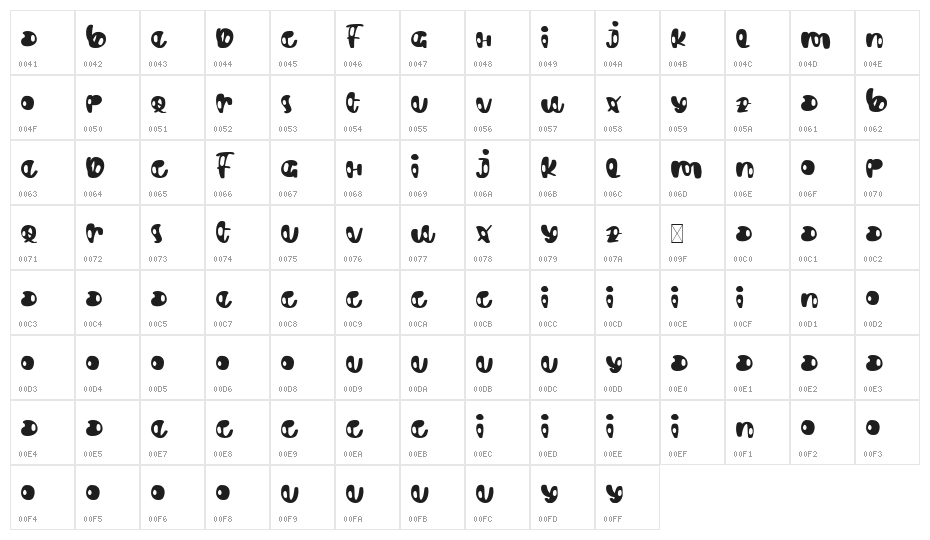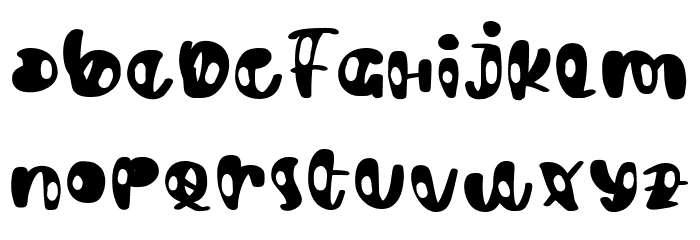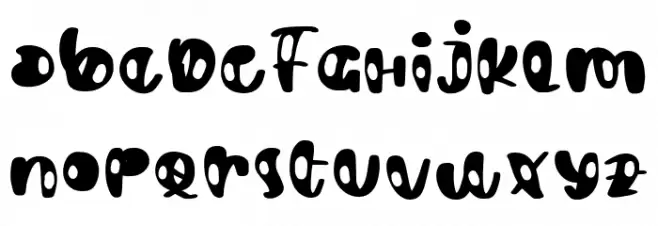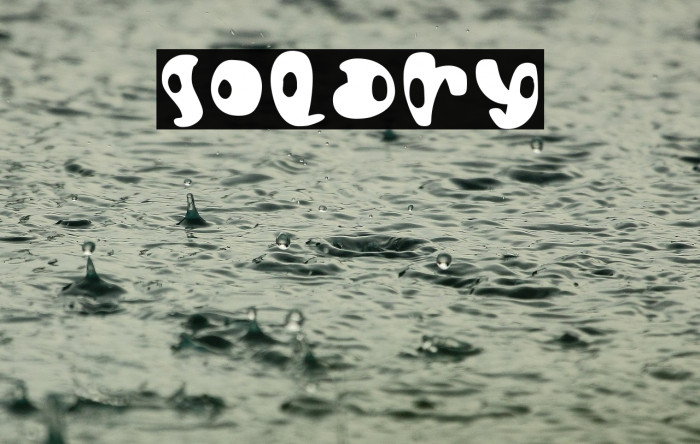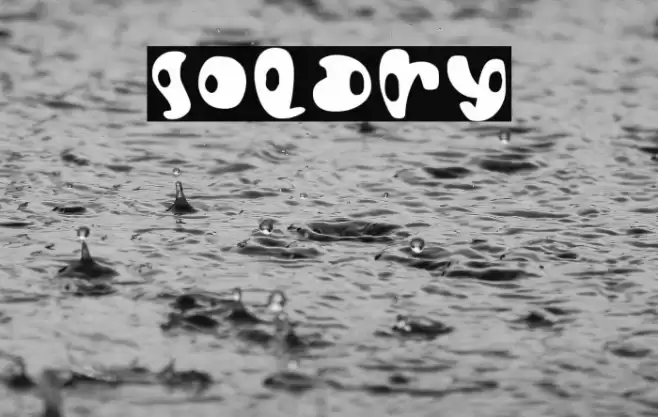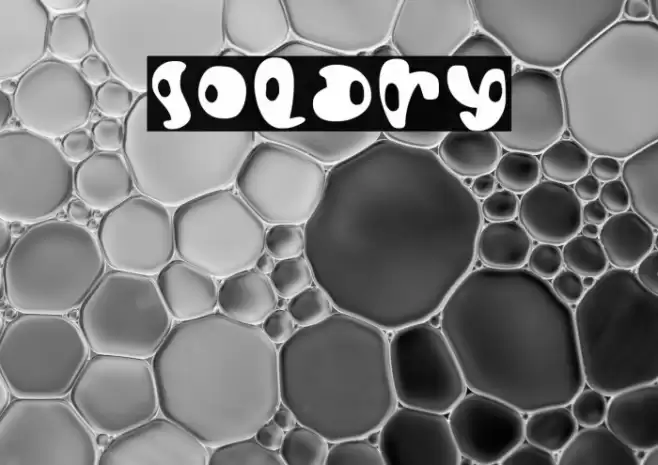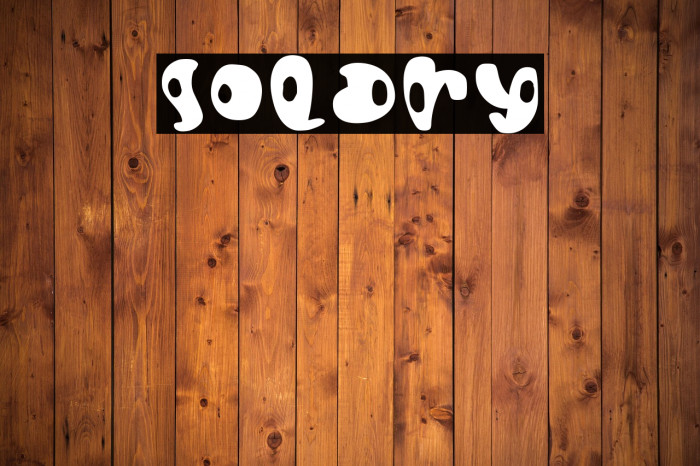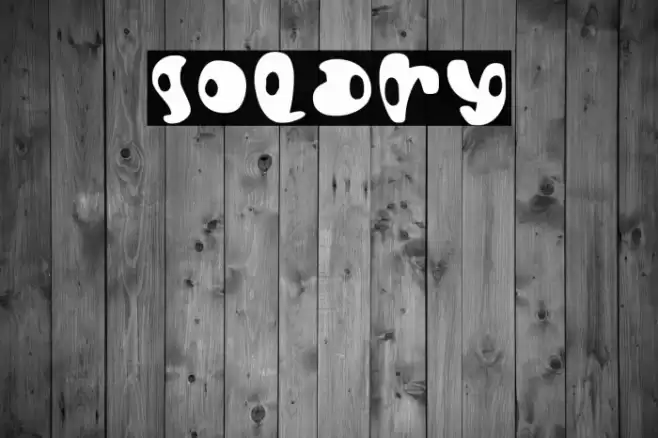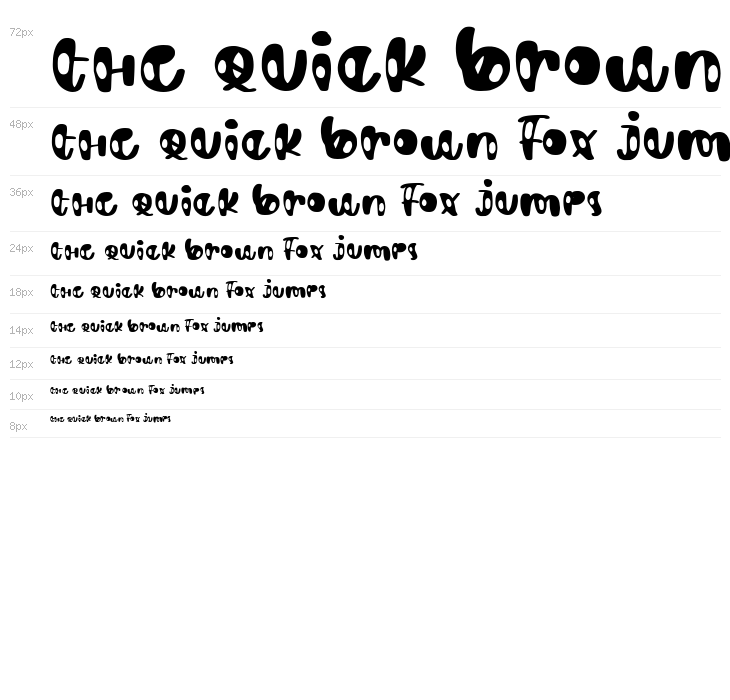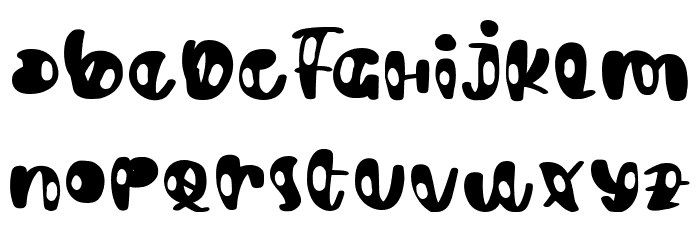
SOLARY Font
✎ Cartoon
| Категория | Cartoon |
| Общий стиль | Playful, Whimsical |
| Область применения | Logos, Headlines, Posters |
| Рекомендуемые проекты | Ideal for children's books, playful branding, party invitations, and creative posters. |